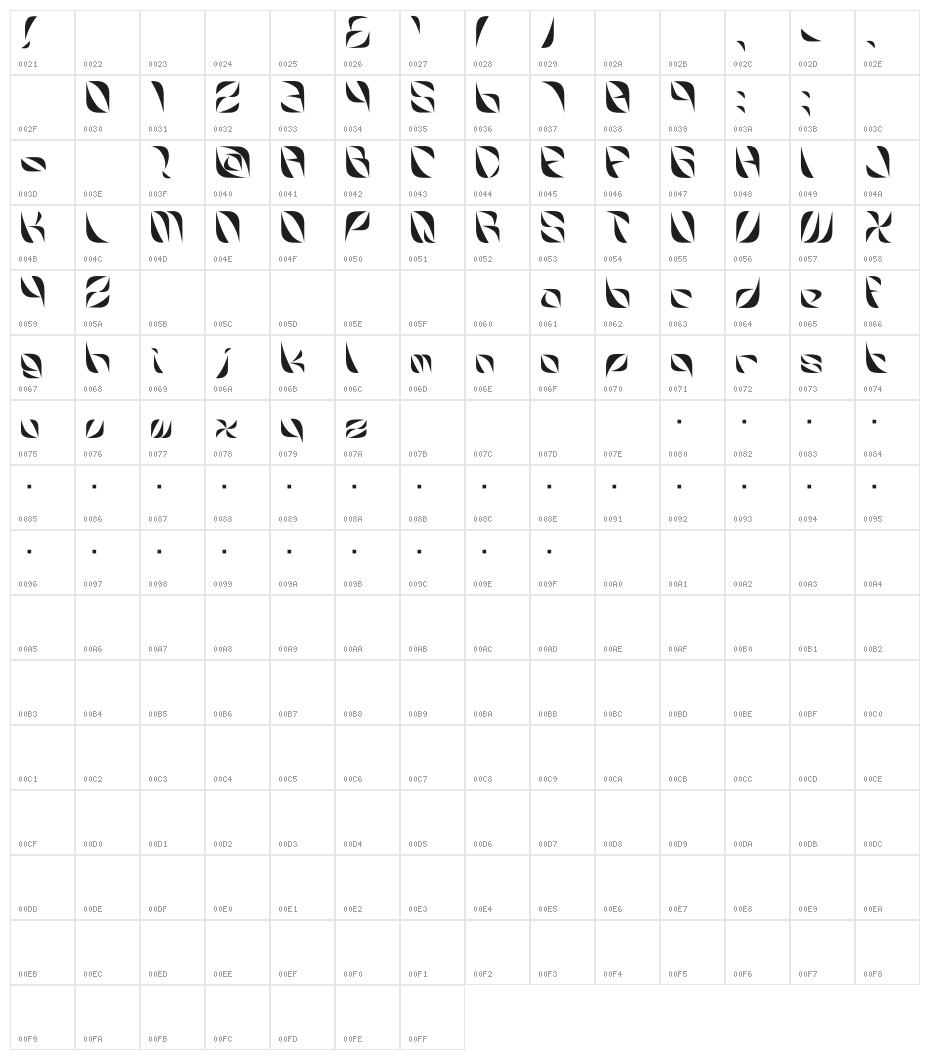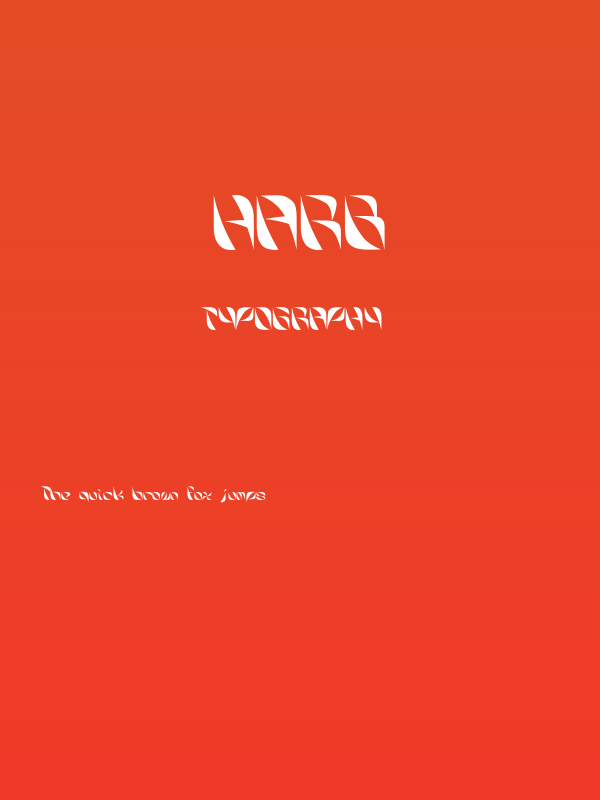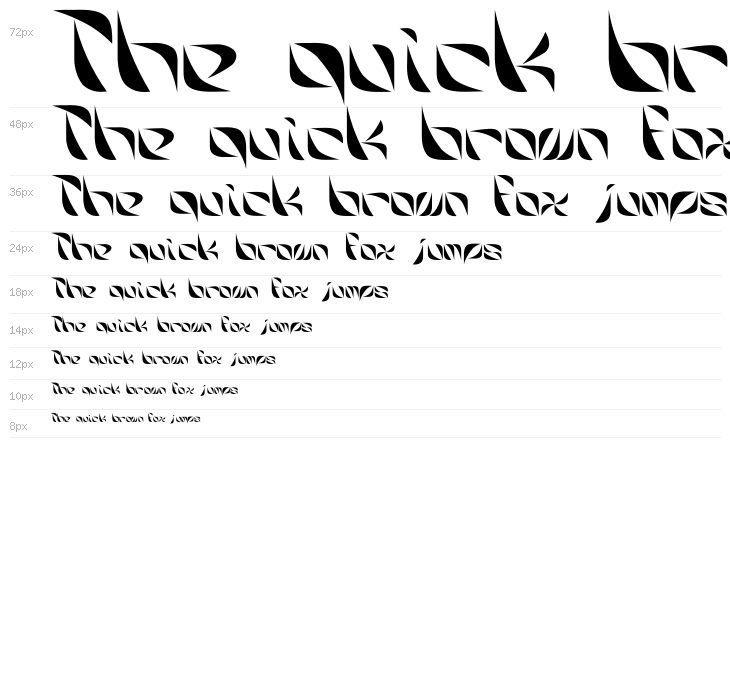
Harb Font
| Stil general | Modern, Decorative |
| Caz de utilizare | Logos, Posters, Artistic projects |
| Proiecte propuse | Ideal for branding, logos, posters, and artistic projects where a unique and bold statement is needed. |